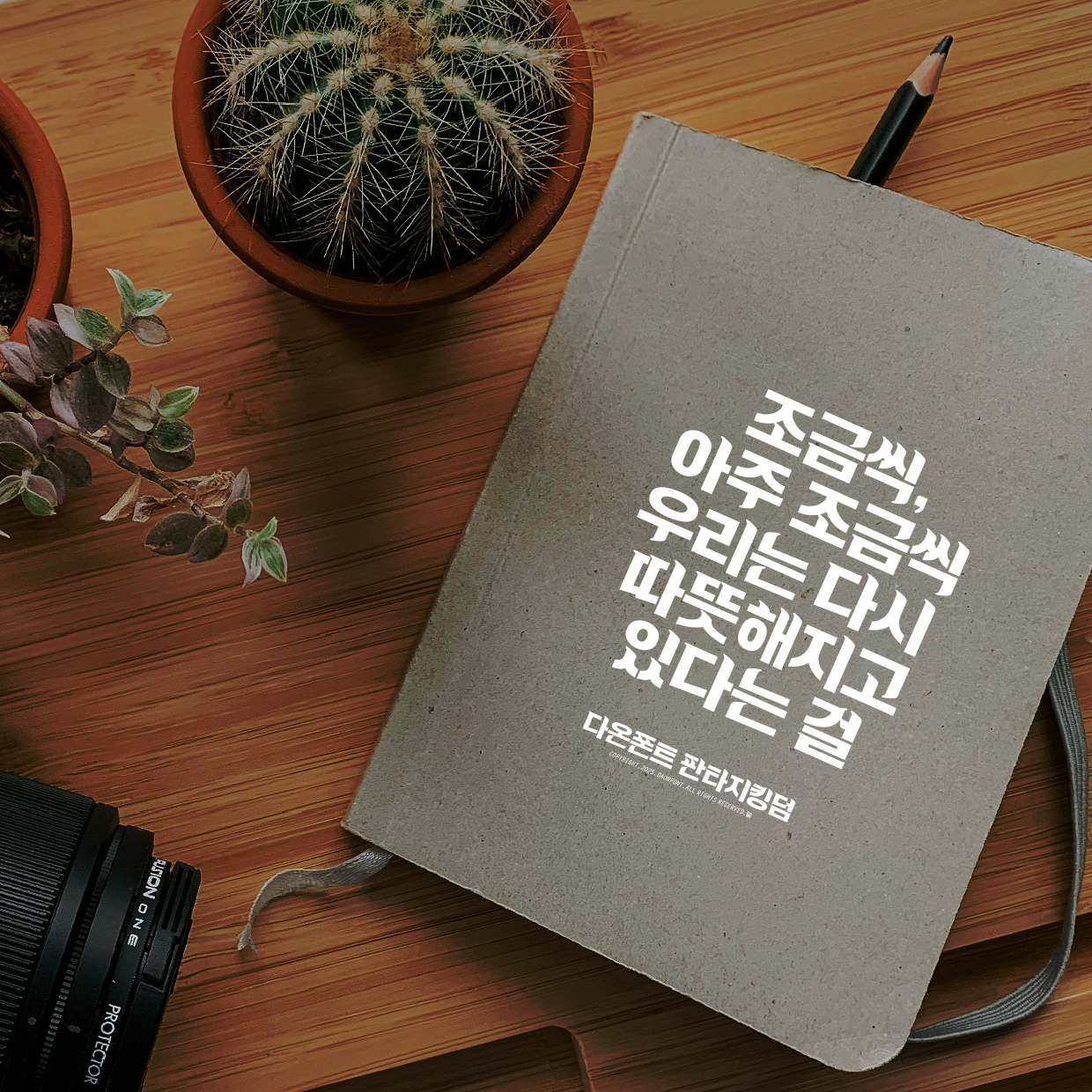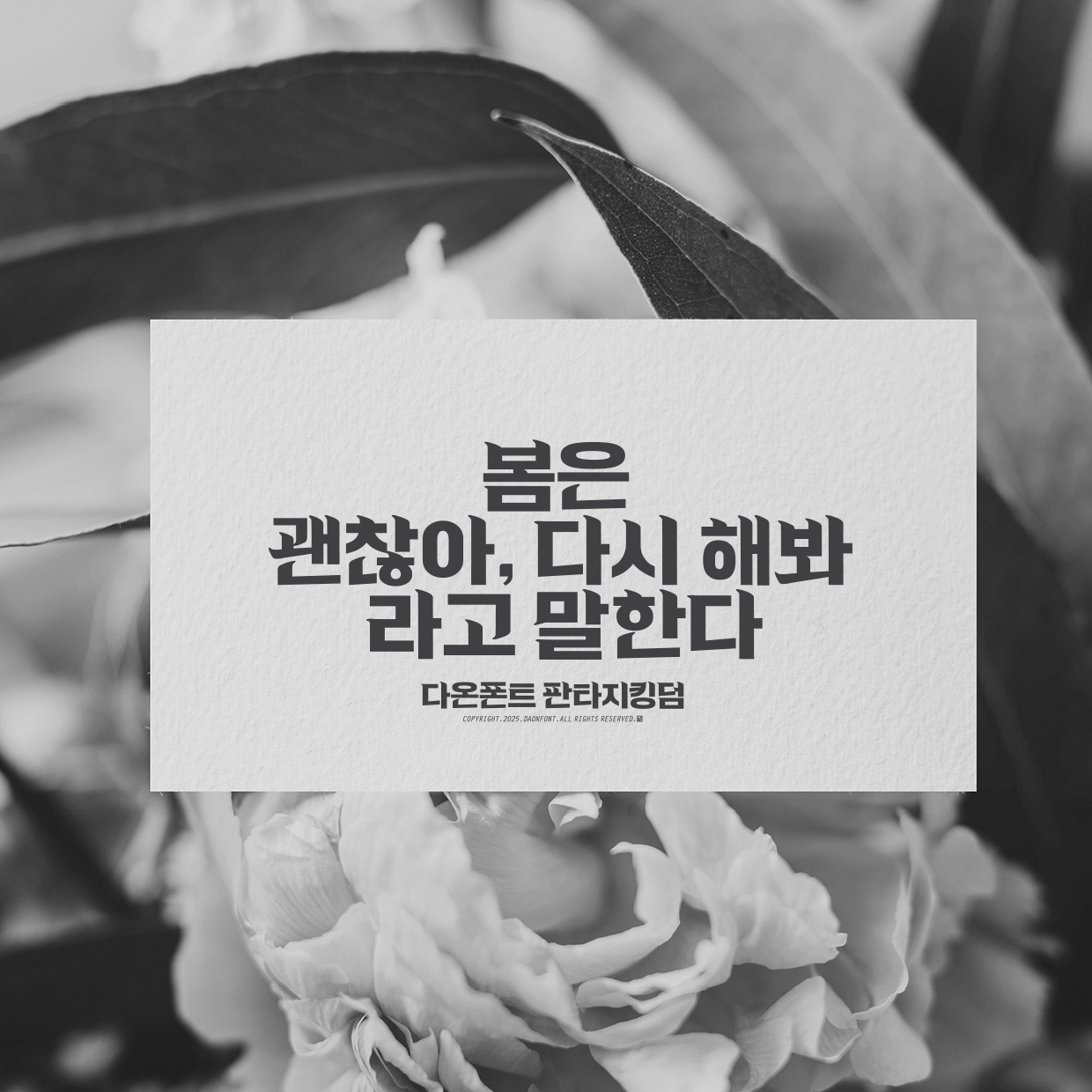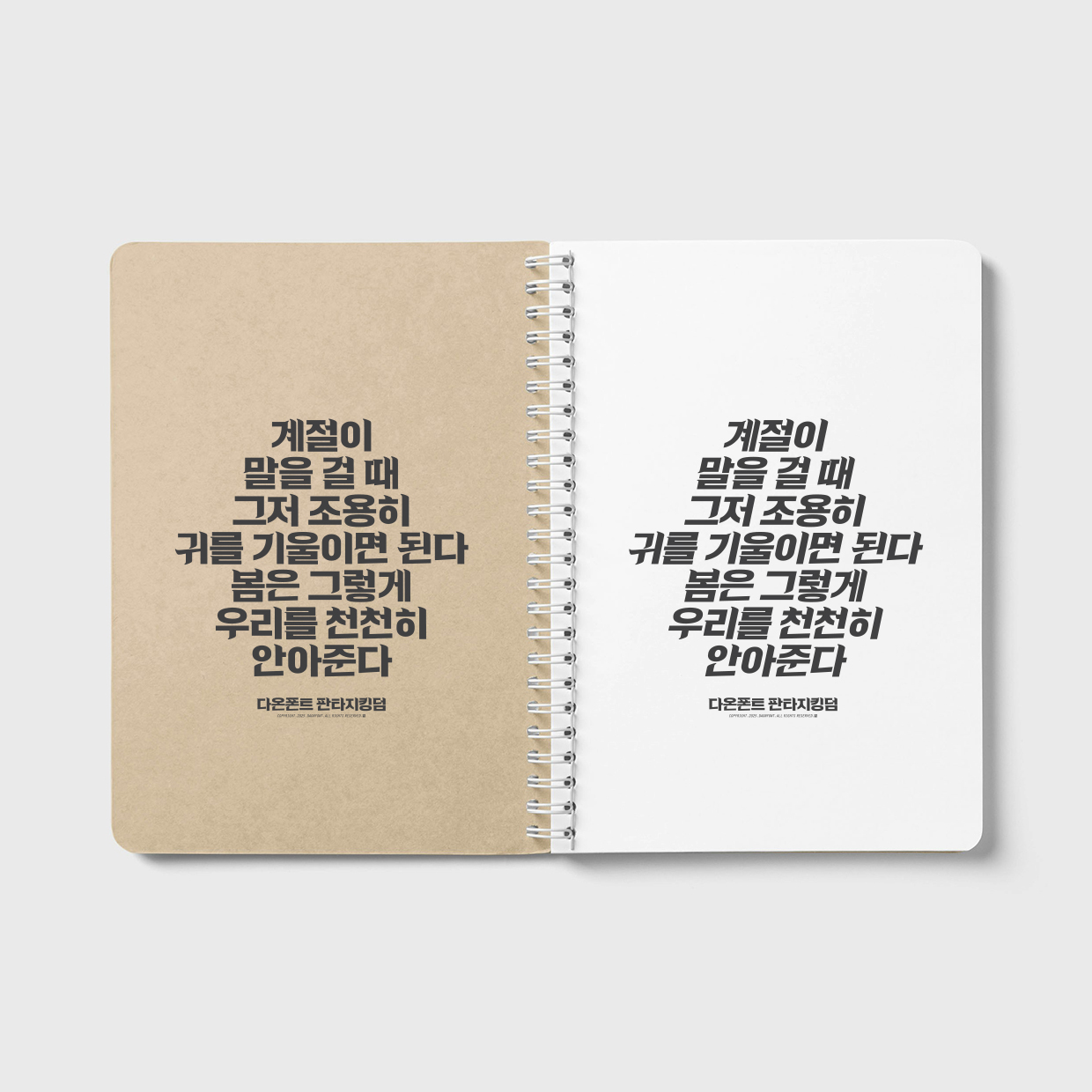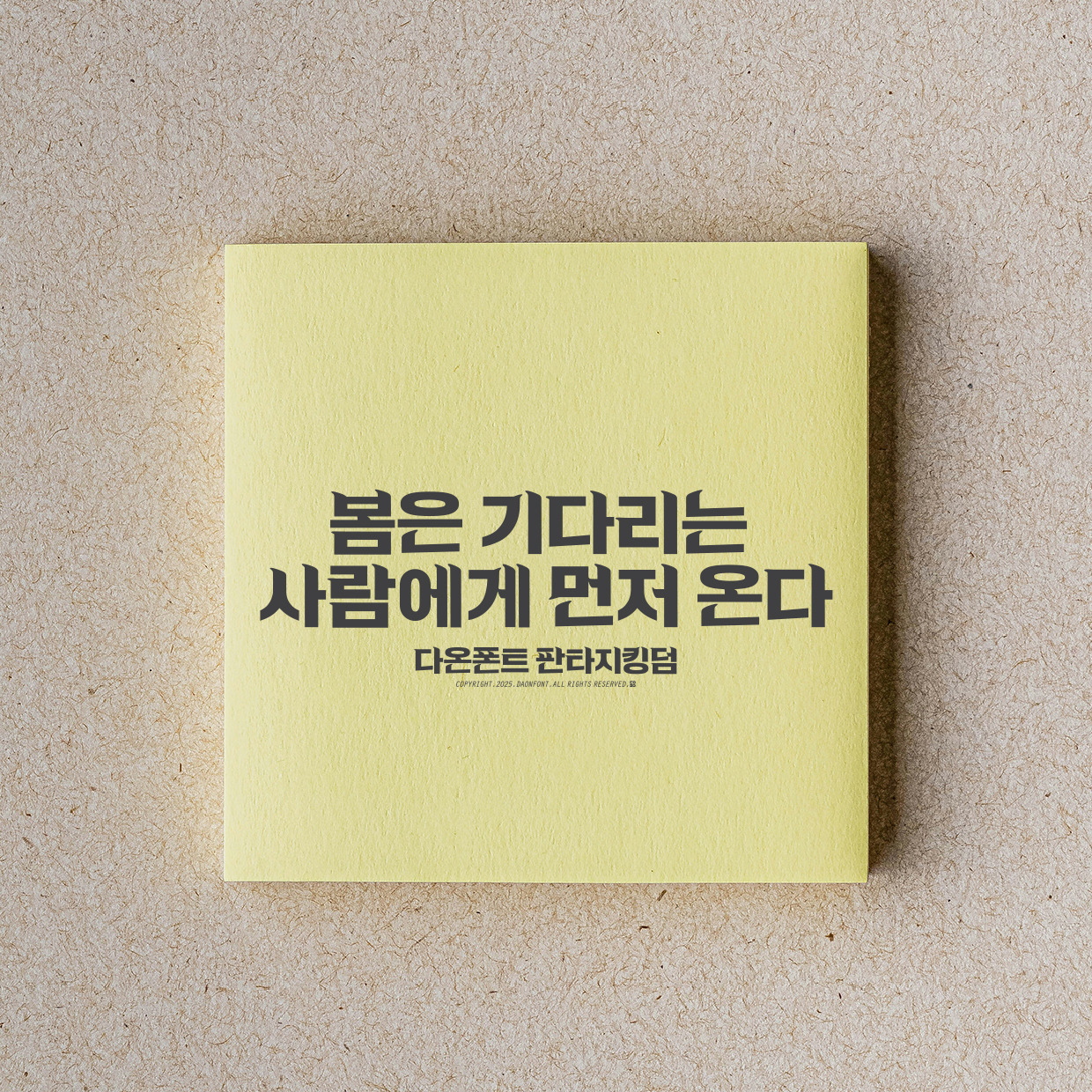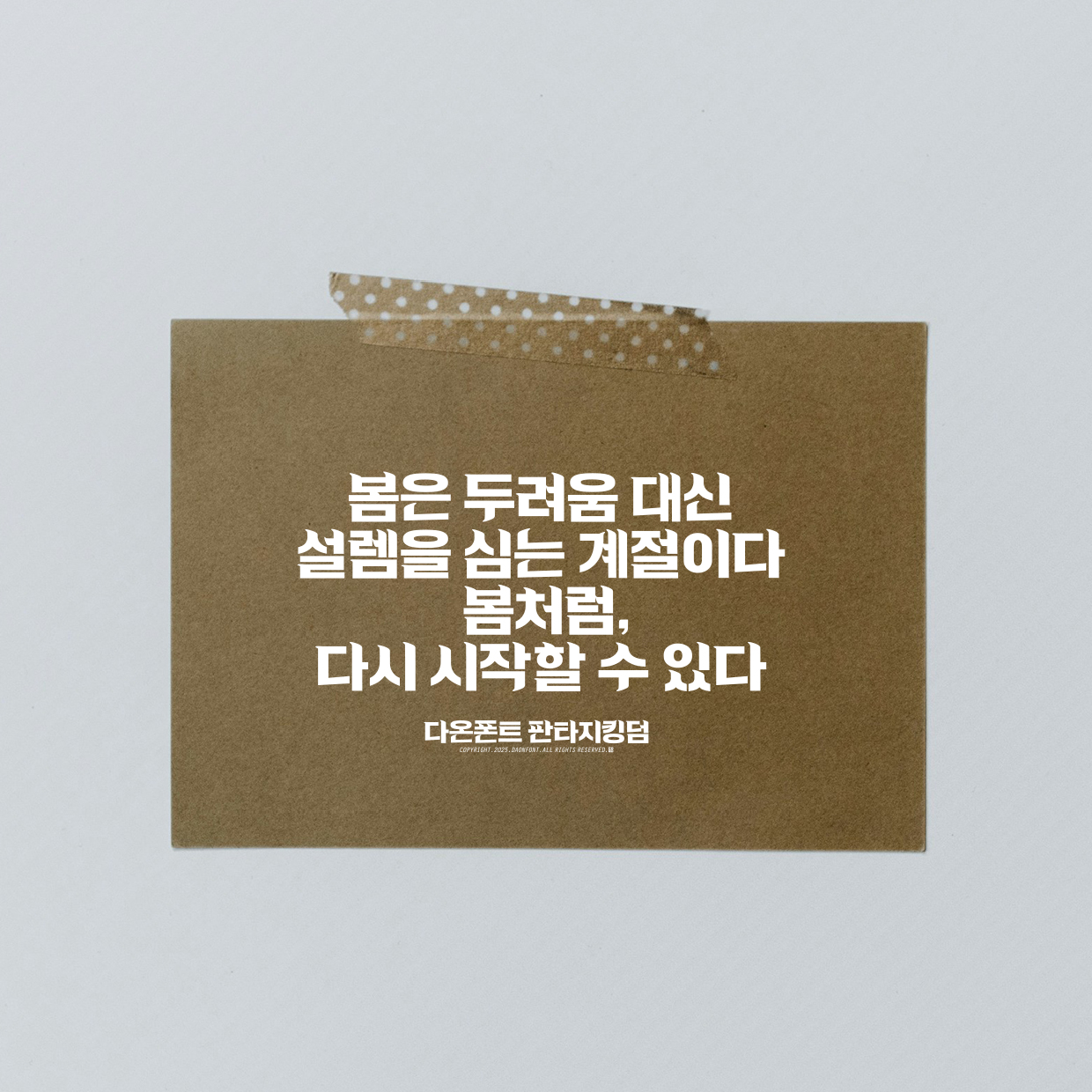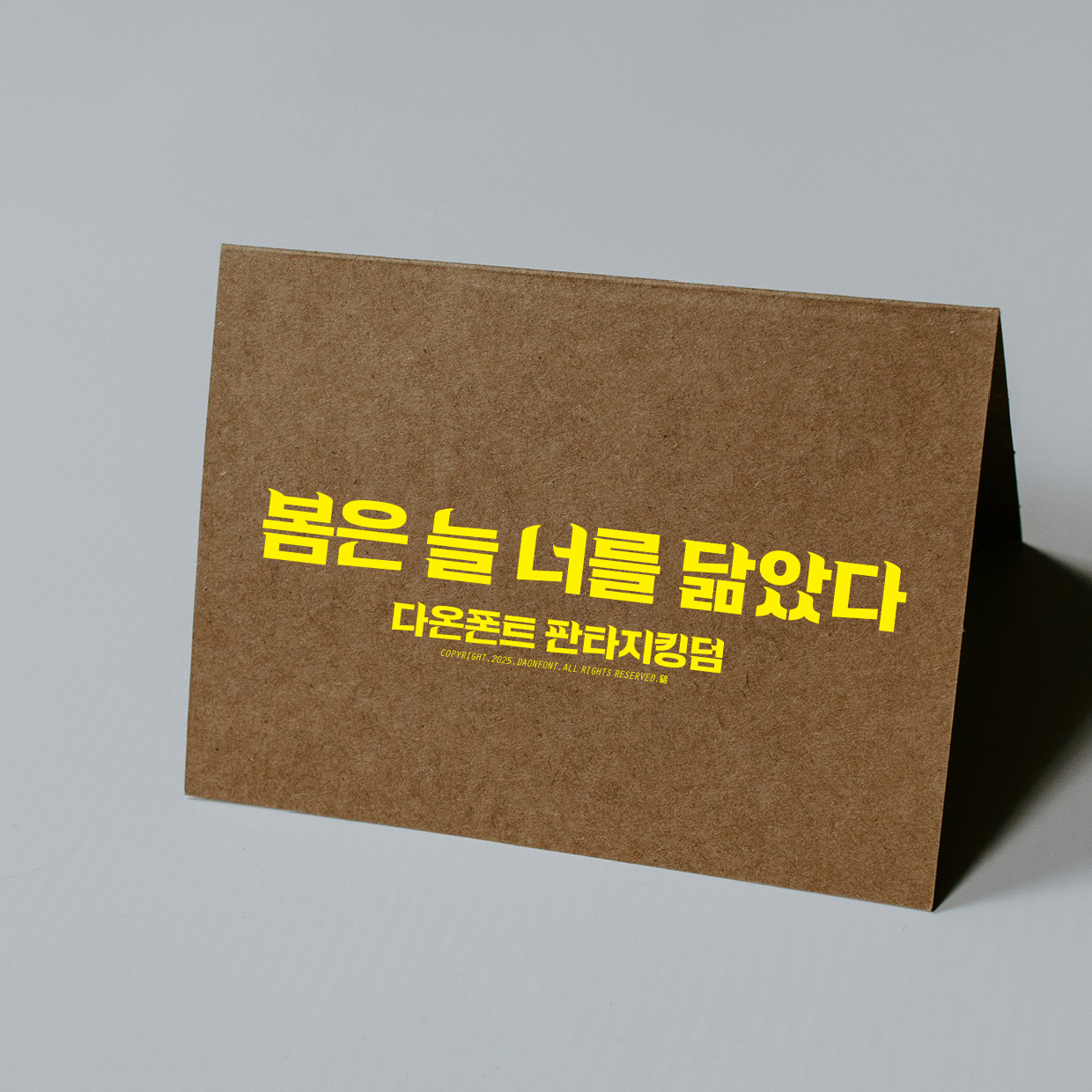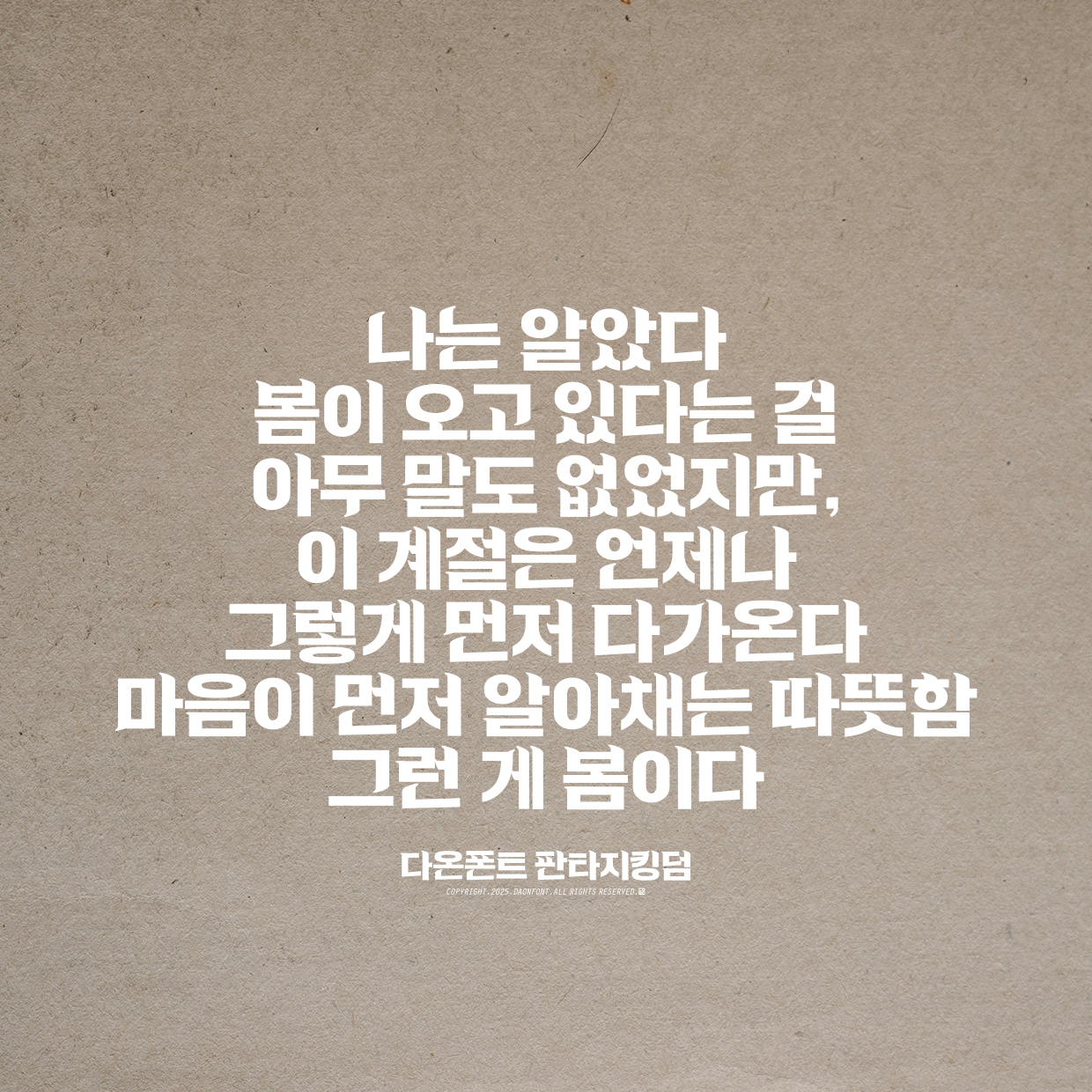
판타지킹덤체 정식 출시 안내
다온폰트의 새로운 서체 판타지킹덤체가
오는 4월 2일(수요일)정식 출시됩니다.
이번 서체는 단순한 디자인을 넘어, 판타지 장르 특유의 서사와 감성을
온전히 담아내기 위해 오랜 시간 동안 깊은 고민과 정성을 기울여 완성했습니다.
왕국의 문장(紋章)처럼 단단하면서도, 이야기의 여백을 담은 듯 유려한 흐름이 공존하는 이 글자들이
누군가의 상상 속 세계에 생명력을 불어넣는 도구가 되기를 진심으로 바랍니다.